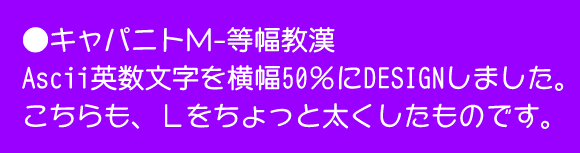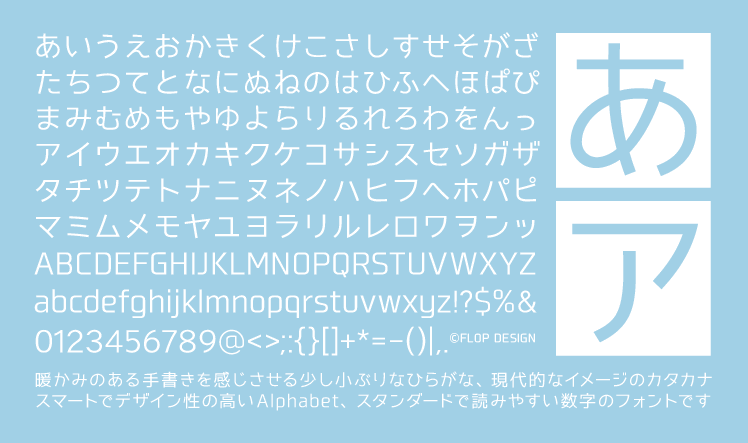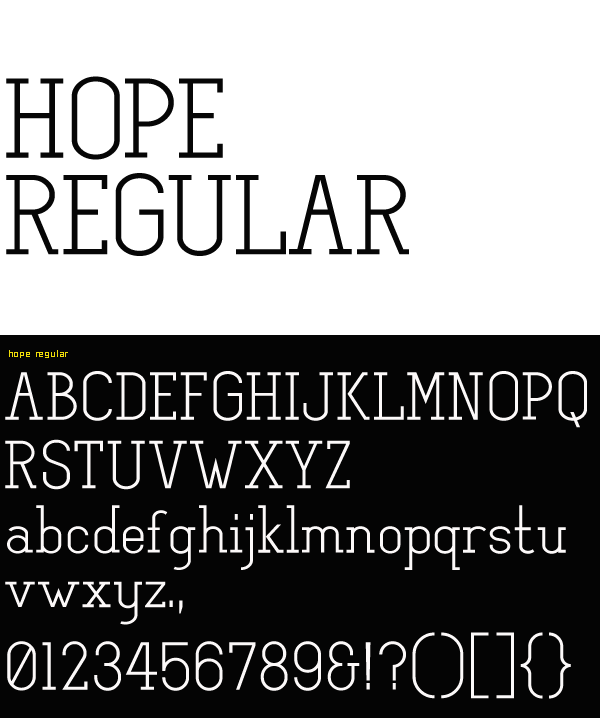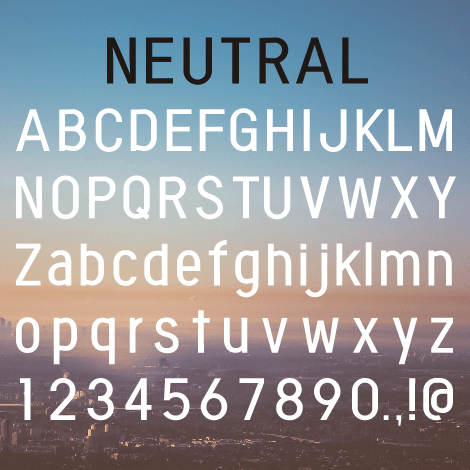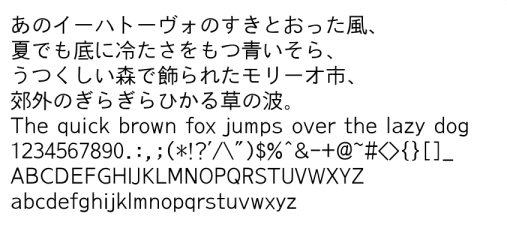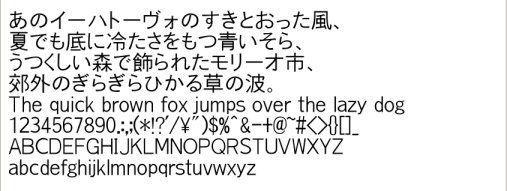
見やすく伝わる資料作りに!読みやすい無料フォント40選
デザインや資料などを相手に見てもらう、読んでもらうためには、読みやすいドキュメント・伝わりやすいデザインにする必要があります。レイアウトの構成も読みやすさ、見やすさの重要な要素ですが、もう1つな大事な要素にフォントがあります。どのフォントを選ぶかで読んでもらう相手への印象が変わってきます。
そこで今回は見やすく伝わるデザインや資料作りにオススメの読みやすいフォントを40個まとめましたのでご参考になさってください。
Corner kana
はっきりとした字体で読みやすいかな・カナフォント。
Hope Regular
レギュラーのウェイトで見やすいフォント。
IPAexゴシック
和文文字(仮名や漢字など)は固定幅、欧文文字は文字幅に合わせた変動幅を基本とした実装を行われ、日本語文書作成の利便性の向上を目指したフォント。ゴシック体ver。
IPAex明朝
和文文字(仮名や漢字など)は固定幅、欧文文字は文字幅に合わせた変動幅を基本とした実装を行われ、日本語文書作成の利便性の向上を目指したフォント。明朝体ver。
KFひま字
WindowsでもMacintoshでも使える、横書き・縦書き対応のOpenTypeフォント。ほのぼの手書きタッチな書体でお手紙を書いたり、お名前シールを作ったり、パソコン画面を和ませてみたりするのに最適。
NEUTRAL
少し縦長でスマートなフォント。
VL Pゴシック
M+ アウトラインフォントベースのモダンゴシック体の日本語 TrueType フォント。
VL ゴシック
M+ アウトラインフォントベースのモダンゴシック体の日本語 TrueType フォント。
あおぞら明朝
7ウェイト展開のIPA明朝ベースの明朝体フォント。
アポロ1
見やすくオシャレなフォント。
あられ-教漢/等幅教漢
切り絵や木版画のような素朴な味わいと、日本文字独特の情感を、直線だけで表現したフォント。
あんずもじ始
教科書体を参考した手書き風フォント。ひらがな、カタカナ、英数字、記号、絵文字のほか、1,006文字の教育漢字を収録。
キャパニトL-教漢
のびのびした明るい線質のフォント。
キャパニトL-等幅教漢
のびのびした明るい線質のフォント。等幅フォントバージョン。
キャパニトM-教漢
のびのびした明るい線質のフォント。ちょっと太めのフォント。
キャパニトM-等幅教漢
のびのびした明るい線質のフォント。ちょっと太めの等幅フォント。